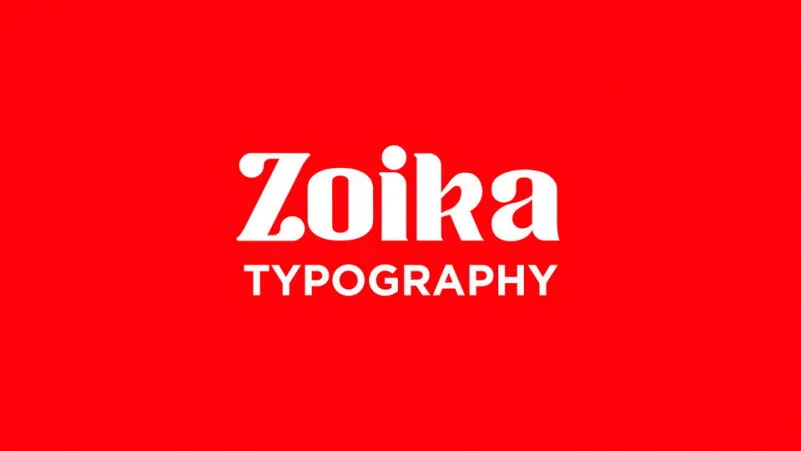
Zoika Typeface – Download Grátis
Olá! Estamos muito felizes com a introdução do Zoika Typeface, uma família serif que incorpora tons de elegância e luxo. Esta tipografia se destaca por oferecer um vasto leque de estilos para atender a uma ampla gama de necessidades de design: moderno, clássico, sofisticado, fashionista, até mesmo serif livre, e decorativo. Este formato de fonte é perfeito tanto para aplicativos digitais quanto impressos. É ideal para criar logos distintivos, headlines poderosas, gráficos publicitários, embalagens de produtos, ou invitations de eventos como casamentos. Com o Zoika Typeface em sua paleta de ferramentas de design, você pode explorar uma infinidade de opções e garantir que suas criações se destacuem. Para designers aficionados em serif, a Zoika oferece estilo refinado e versatilidade, fazendo-a perfeita para qualquer projeto. O Zoika Typeface é um verdadeiro atalho para criar design impecável.